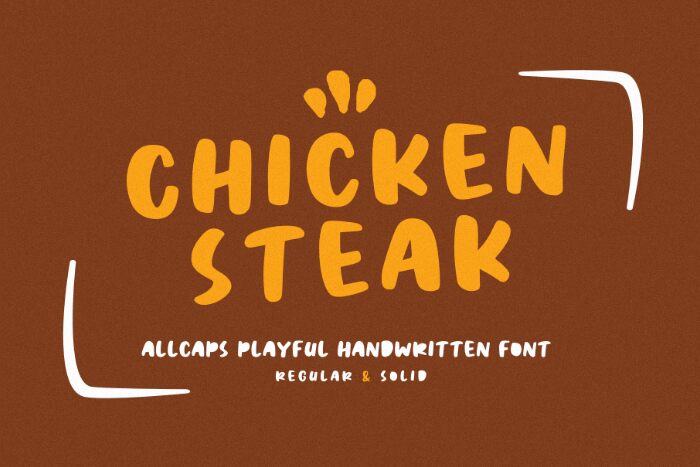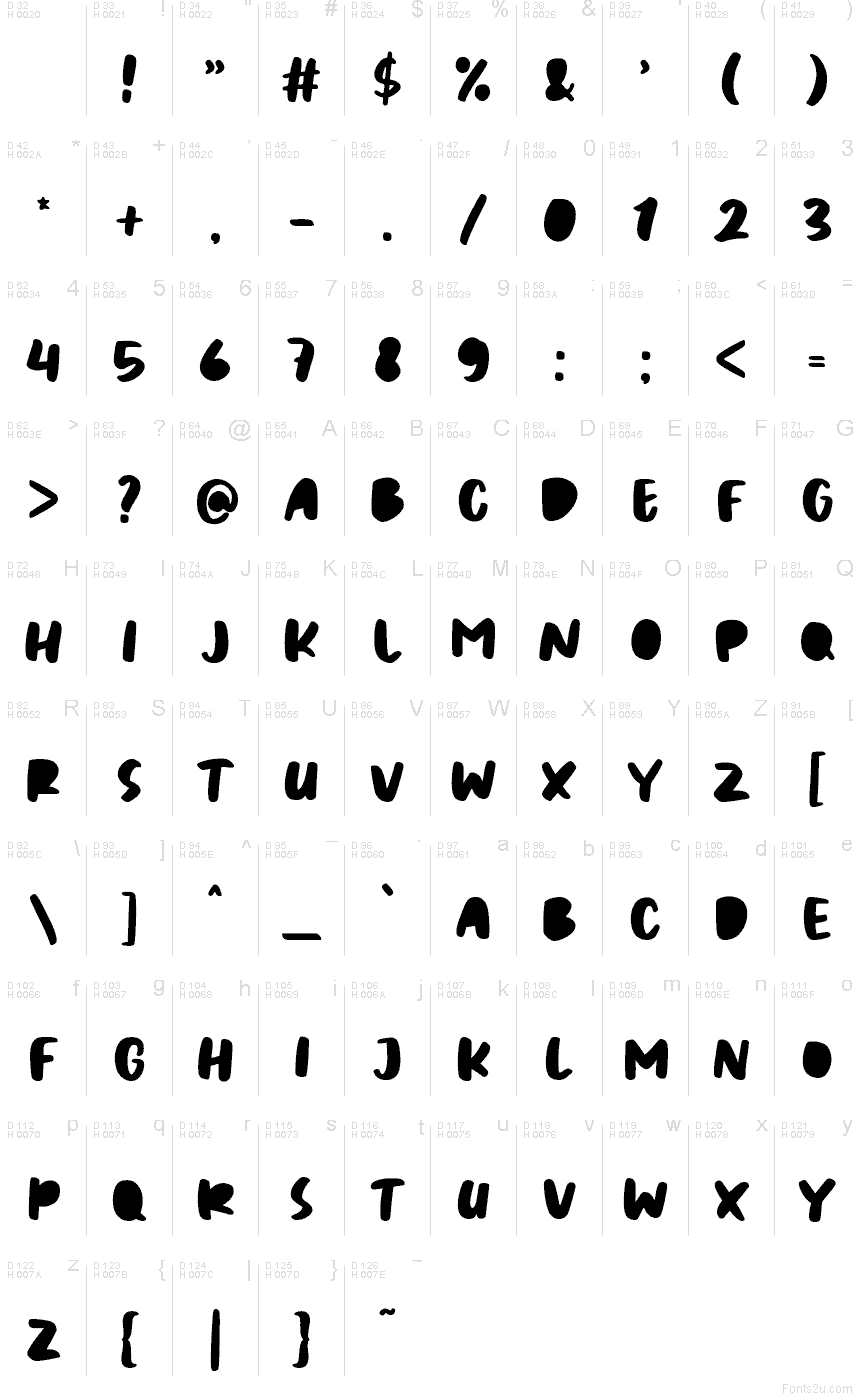
Chicken Steak Solid de Madatype Studio es una tipografía de rótulo de estilo cartoon gratuita, con mayúsculas gruesas dibujadas a mano y un dinamismo alegre. Los trazos anchos se ensanchan y afinan de forma irregular, con extremos rombos y uniones profundamente curvadas. Las formas inclinadas y las alturas irregulares mantienen el diseño de las letras vivo y desenfadado.
Se dirige directamente al público infantil y familiar. Sus formas amigables son ideales para envases de juguetes, carteles de cumpleaños, tarjetas de título animadas y marcas de alimentación informales en estanterías o pantallas. Las esquinas redondeadas y el ritmo ascendente y descendente de las letras recuerdan a personajes ilustrados, mascotas de menús o gráficos de productos lúdicos.